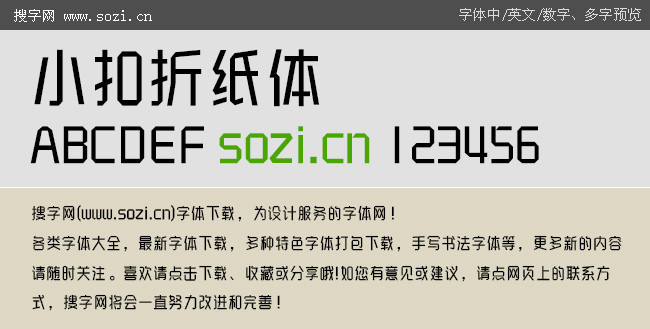
小扣折紙?bào)w
搜字網(wǎng)提供一款小扣折紙?bào)w字體下載,小扣折紙?bào)w是一款卡通字體。字形瘦高,字體轉(zhuǎn)折處做成了紙張折疊的效果,非常具有趣味性,適合海報(bào)設(shè)計(jì)、包裝設(shè)計(jì)等廣告設(shè)計(jì)場(chǎng)合使用。